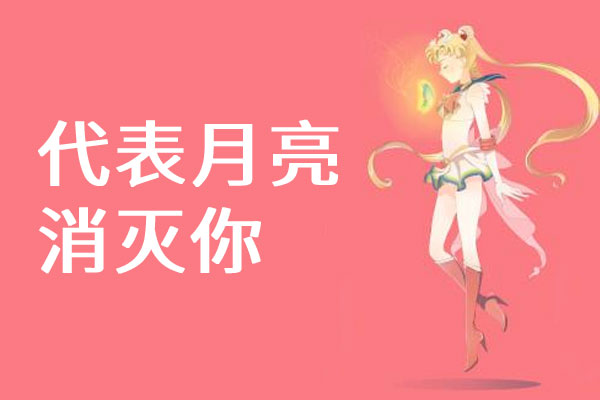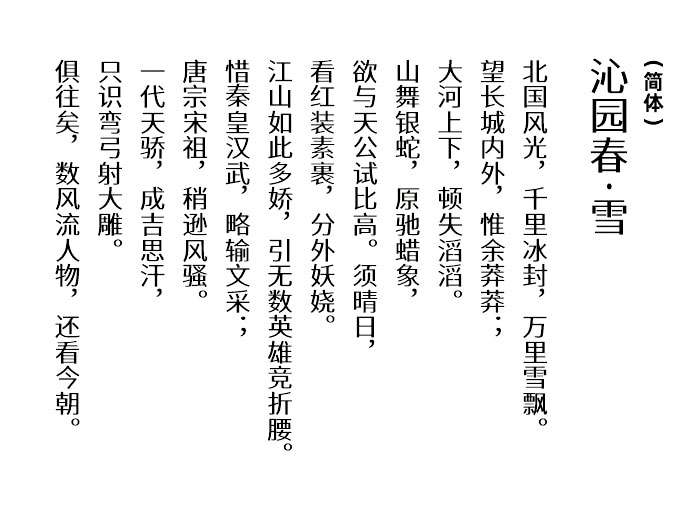
江城正义体
江城正义体是国内字体爱好者刘鹏在思源黑体的基础上进行改造的一款字体。通过把横笔调细、纵笔调粗的方式,使字体更富有现代感。这款字体适合用于海报标题、LOGO等方面的设计,也可以方便地进行二次创作。
江城正义体符合中国大陆的习惯,包含了完整的字符和五个不同的字重,无论是简体还是繁体,都能找到相应的字符。
江城正义体效果预览
江城正义体字体效果预览